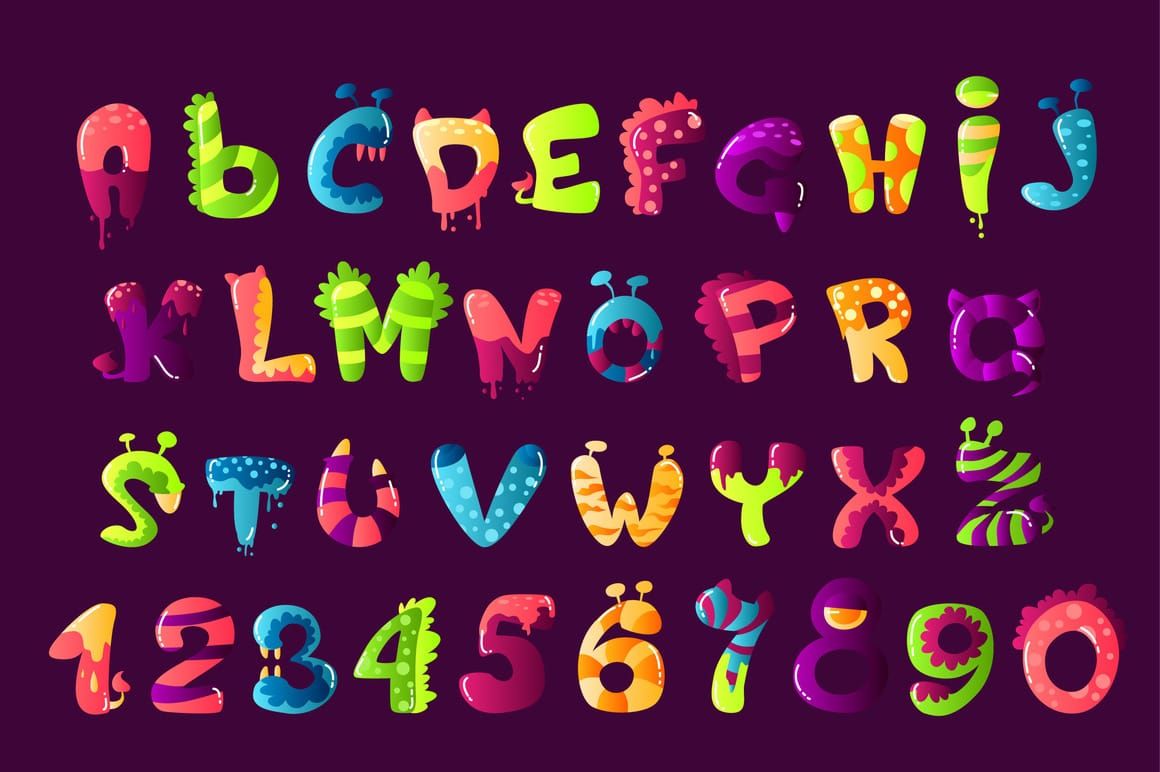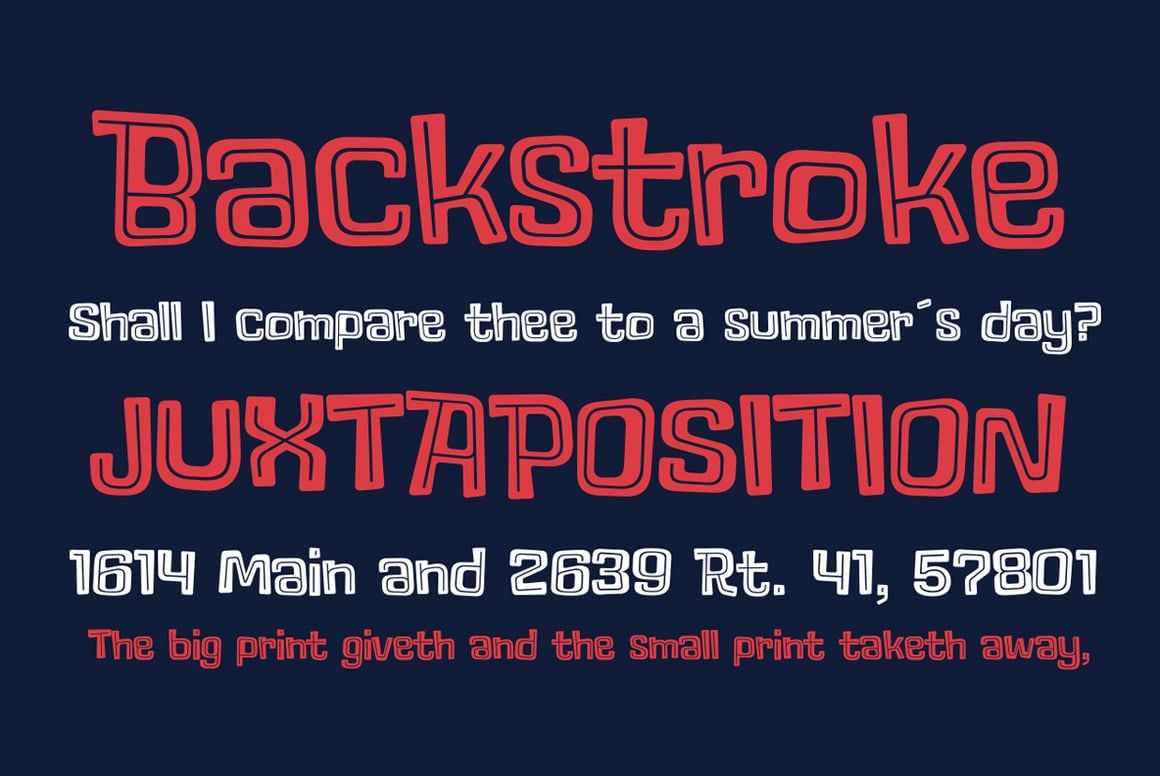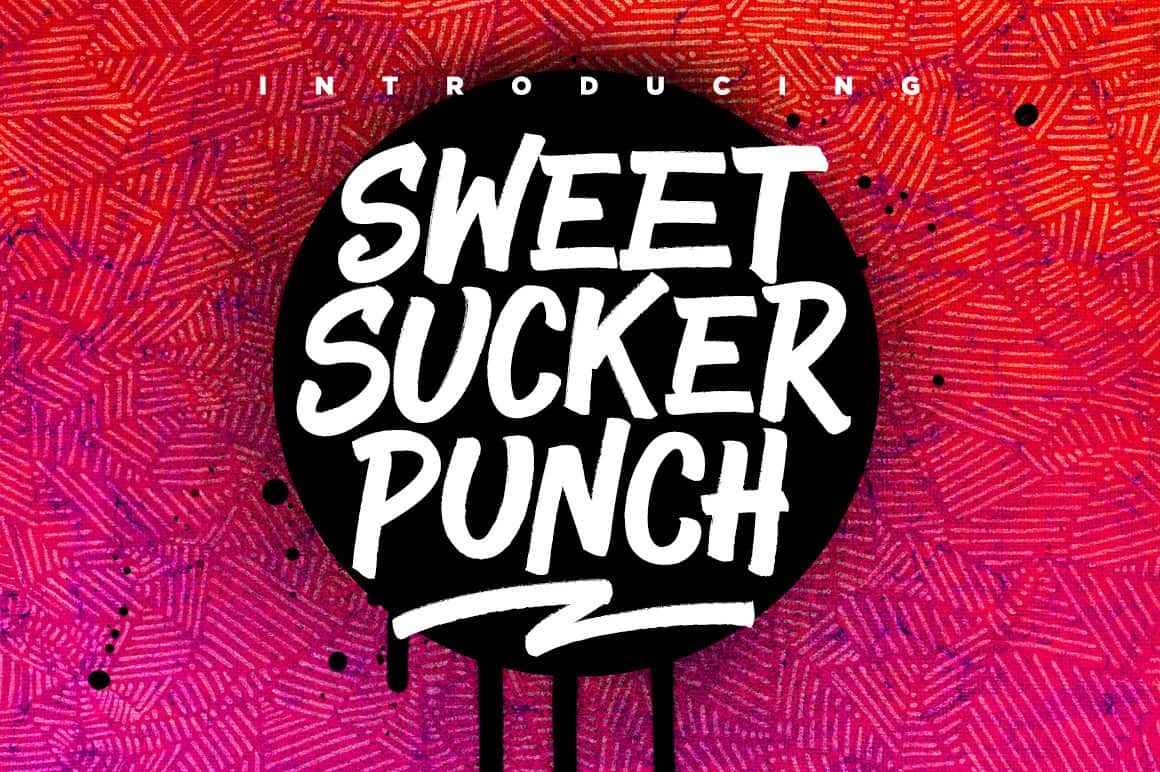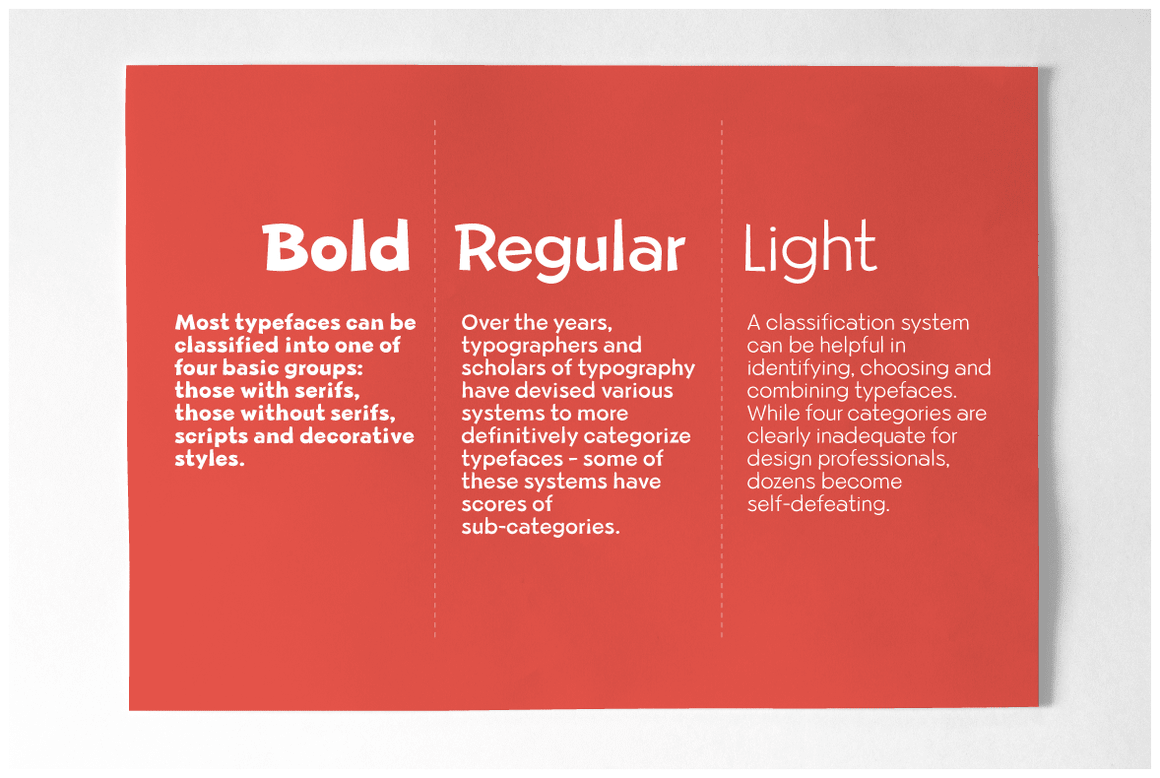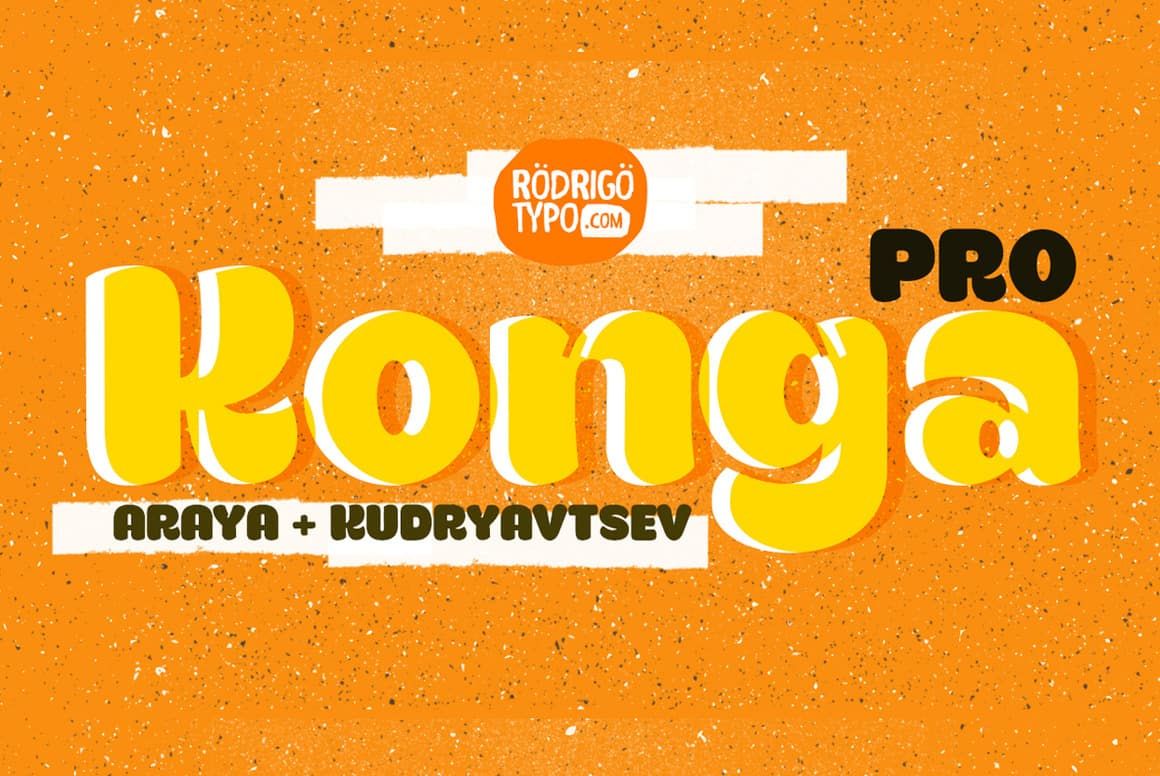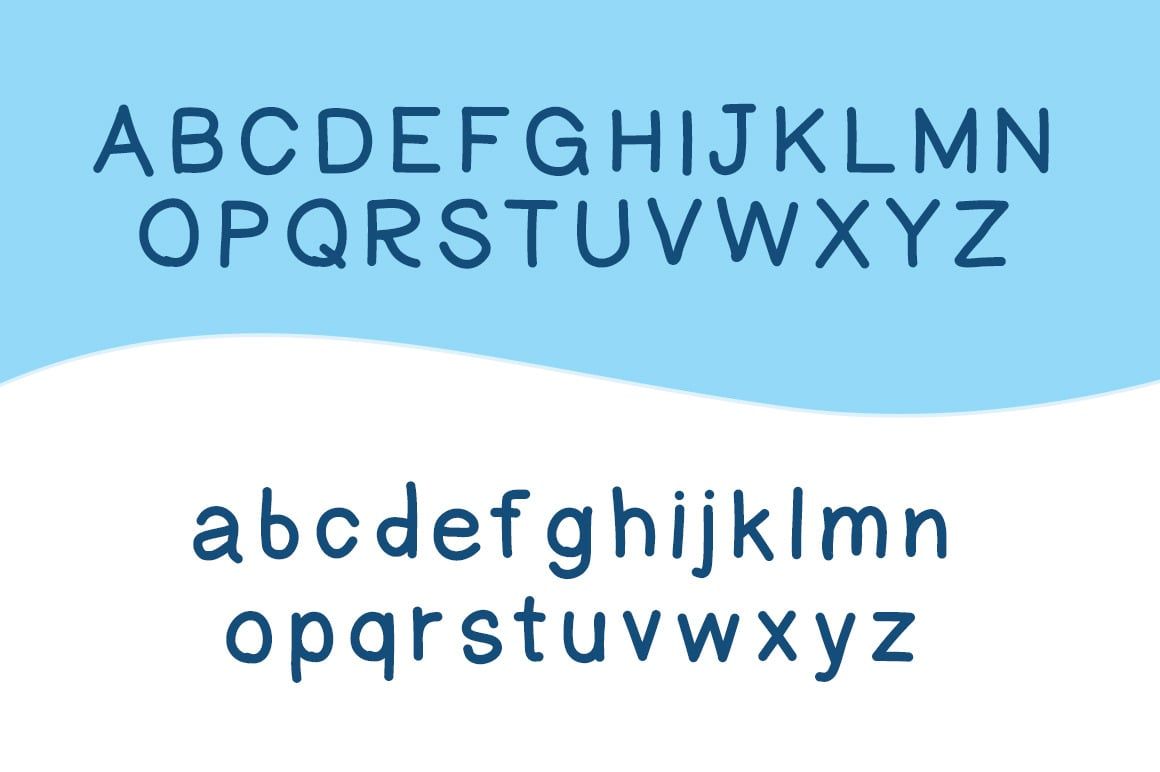
20 fuentes de cómic creativas que puedes tener
Desde memes se hizo popular en línea, de repente todo el mundo tenía una salida para sus opiniones. Lo interesante de memes es el hecho de que nunca es sencillo. Necesita ingenio y un montón de creatividad para que funcione.
Por supuesto, memes no se trata solo de la broma o del comentario lleno de sarcasmo. También se trata de crear una imagen que represente el mensaje a la perfección.
La elección de la imagen perfecta suele ser lo más destacado. Pero la fuente también juega un papel vital, por lo que no puede simplemente elegir una fuente genérica y esperar que su meme tenga el impacto que está buscando.
Por qué su fuente es importante
Pero es solo un meme. Puedes usar cualquier fuente, ¿verdad?
Sí, puede utilizar cualquier fuente que desee. Pero esto puede afectar la forma en que las personas reaccionan a tu meme. Especialmente si buscas algo completamente teatral, no puedes esperar que una fuente simple funcione. Tiene que ser tan dramático como el mensaje que está tratando de transmitir.
Considerando el hecho de que memes Por lo general, se utilizan para hacer bromas, las fuentes de cómic podrían ser la solución perfecta si cree que falta algo en el meme en el que está trabajando.
Verá, al igual que cualquier otra pieza de diseño gráfico, cada elemento y aspecto del diseño tiene que trabajar entre sí. No puede limitarse a una broma divertida y luego tener un fondo aburrido y un estilo de fuente igualmente aburrido. De la misma manera, no puede esperar que su broma divertida y su fondo divertido funcionen si su fuente es incorrecta.
Elegir tu fuente de cómic
Lo mejor de las fuentes de cómic es que hay muchos estilos para elegir. Algunas son más sencillas que otras, perfectas para quienes quieren un look clásico. Estos son los tipos de fuentes de cómic con las que crecimos, las que a menudo verías adornando las páginas de la tira cómica dominical.
Algunas fuentes son más grandes que la vida, creando un efecto dramático. Estas fuentes son para memes creado para captar la atención de cualquier persona en un instante. Son los que te gritan en el momento en que aparecen en tu pantalla.
Por supuesto, también debes asegurarte de que tu fuente de cómic tenga una personalidad distinta. Especialmente si haces memes de forma regular, la fuente que elijas debe ser la tuya.
Fuentes de cómic pensadas para memes impresionantes
Encontrar la fuente de cómic perfecta requiere obtener toda la inspiración que puedas. Aquí hay algunas fuentes de cómics geniales que te harán comprender lo que se necesita para hacer que tu meme sea realmente explosivo.
Fuente Superfruit
Superfruit es una fuente de visualización sabrosa y saludable, con mucha diversión y actitud. Perfecto para carteles, folletos, invitaciones, logotipos y más.
Sándwich de héroe
Dale un mordisco al crimen y haz que el metro vuelva a ser seguro con la tipografía Hero Sandwich.
Familia Lechero
Milkman es una divertida fuente con todas las funciones en tres pesos: ¡Ligera, Regular y Negrita!
Konga Pro
Konga es una tipografía que se diseñó en 2012, paso tiempo y vuelvo a rediseñar y mejorar una tipografía más que ahora incluye cirílico y alternativas.
Pantalla Fleischer
Fleischer es un tipo de letra de pantalla áspero y lúdico bueno para titulares y carteles. La cara se basa en formas de letras históricas combinadas con letras enérgicas de estilo pulpa del siglo XX.
Galpon Family
Terrible
Inspirado en la película de terror clásica y el cómic vintage. Los mejores usos de Dreadful Typeface para encabezados, tipo de logotipo, citas, diseño de ropa, invitaciones, folletos, carteles, tarjetas de felicitación, empaques de productos, tapa del libro , citas impresas, álbum de portada, película, etc.
Beebzz
Beebzz es una familia de fuentes original diseñada para titulares, títulos y subtítulos. La fuente te devuelve a esos tiempos perfectos, cuando no había necesidad de ser serio, cuando el mundo entero no era tan serio. Tiene su propio estilo único expresado en perfectas formas condensadas, inspirado en la caligrafía infantil a mano alzada y en fuertes tipos de letra geométricos.
Tipografía Thunder Pants
Creado con bordes redondeados, este divertido tipo de letra retrata el estilo de cómic y superhéroe de la vieja escuela. Todas las letras mayúsculas incorporan el rayo, mientras que las minúsculas son formas de letras normales para mantener sus usos amplios.
Yeti
Yeti es una fuente divertida y muy fácil de leer. Es ideal para libros y carteles para niños. Viene con letras mayúsculas y minúsculas y un montón de signos diacríticos.
PAUD
Aporta más historia a tus creaciones con este tipo de letra feliz. Se inspiró en los garabatos de los niños y en algunas redes sociales. pegatinas .
Ponche dulce de lechón
Sweet Sucker Punch es un marcador ruidoso, orgulloso y contagiosamente divertido. lápiz fuente que gritará su mensaje desde los tejados.
JollyGood Proper Essentials
JollyGood propiamente dicho es un tipo de letra divertido y amigable que es lo suficientemente limpio como para usarlo en textos más largos. Es una familia de 4 fuentes que cubre todas sus necesidades esenciales. Tiene un conjunto de caracteres asombroso, con soporte para la mayoría de los idiomas europeos, así como alternativas y ligaduras.
Fevhil